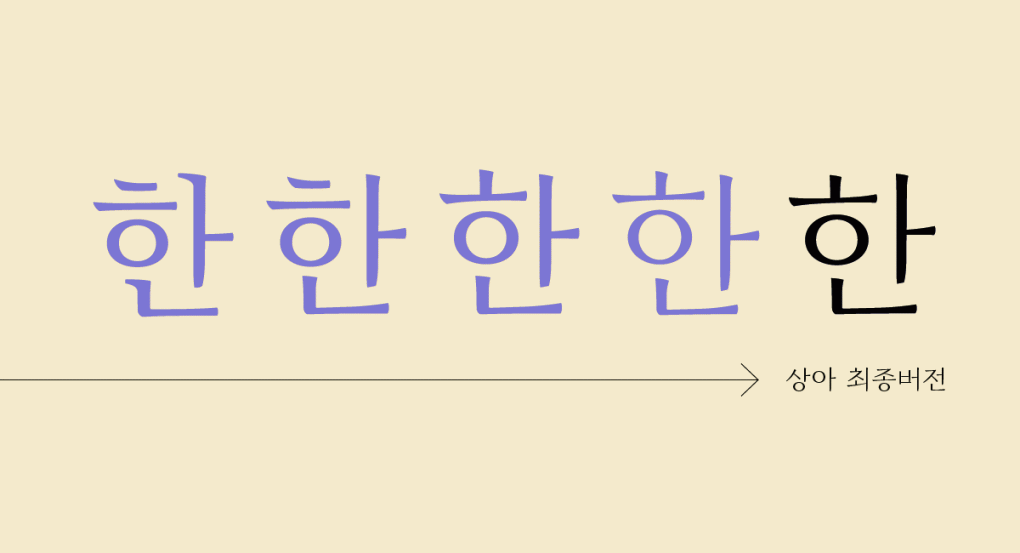
폰트와 함께 세상을 탐험하는 폰트 디자이너, 이주현
Q. 안녕하세요. 코스모프타입 이주현 디자이너님, 간단한 소개 부탁드립니다!
안녕하세요. 코스모프타입 디자이너 이주현입니다. 코스모프타입은 다양한 시각 실험을 통해 폰트를 만들고 있습니다. 주로 폰트를 조판했을 때 만들어지는 새로운 질감에 집중하며 작업하고 있습니다.
Q. 와, 문장이 멋져요. 새로운 질감에 대해 조금 더 설명해 주실 수 있나요?
예를 들어, 같은 텍스트를 각기 다른 폰트로 썼을 때를 상상해 볼게요. 같은 부리체(세리프)로 쓰더라도 부리의 둥근 정도, 굵기, 길이, 여백에 따라서 지면(화면)의 질감이 달라진다고 생각해요. 그래서 처음 폰트를 기획할 때도 작은 요소들이 텍스트로 써졌을 때 보이는 느낌을 관찰하는 편이에요. 「상아」의 경우에는 획 끝이 모두 뾰족하게 되어있어요. 하지만 질감이 너무 가시같이 느껴지지 않았으면 했고, 좀 더 중화할 수 있는 몇 가지 장치들을 넣었습니다.
Q. 가을 달처럼 풍부한 여백과 예스러운 구조를 가진 폰트, 「상아」를 디자인하면서 제일 신경 쓰셨던 부분은 무엇인가요?
한글 구조를 잡는 게 가장 어려웠던 것 같아요. 부리가 아주 작아서 부리체, 민부리체 사이 그 어딘가에 있는 구조로 만드는 것이 어려웠습니다. 또, 대각선 있는 획 (ㄱ,ㅅ) 느낌을 많이 고민했습니다. 비침의 각도나 둥근 정도를 다각도로 실험해봤던 것 같아요. 여러 가지 버전이 있었는데, 최종적으로 지금의 형태가 되었습니다.
Q. 「상아」를 어떻게 사용하면 좋을까요?
소설이나 자기계발서 같은 종이책의 본문도 상상해 보았고, 유튜브 썸네일 제목이나 자막에서도 사용하면 좋을 것 같아요.
Q. 폰트 디자이너들이 폰트를 자기 본인으로 생각하는 때도 있잖아요.작업을 잘하는 사람들을 보면 곧 자기를 사랑하는 사람이라는 생각이 들어요. 폰트 디자이너로서 바라는 점이 있으신가요?
폰트는 공기와 같다고 하잖아요. 잘 드러나지 않음에도 요즘 많은 분이 폰트 디자인에 관심을 가져주시는 것 같아 좋아요. 수업을 듣거나 직접 만들어보는 분들도 많고요. 스티브 잡스가 대학 타이포그래피 수업을 듣고 애플 제품에 멋진 폰트를 탑재한 것처럼, 폰트에 관한 관심이 언젠가는 꼭 쓸모가 있을 거라 확신해요. 공기처럼 너무 사소하지만 잊지 않고, 앞으로도 많은 관심과 애정을 주시면 좋겠어요.